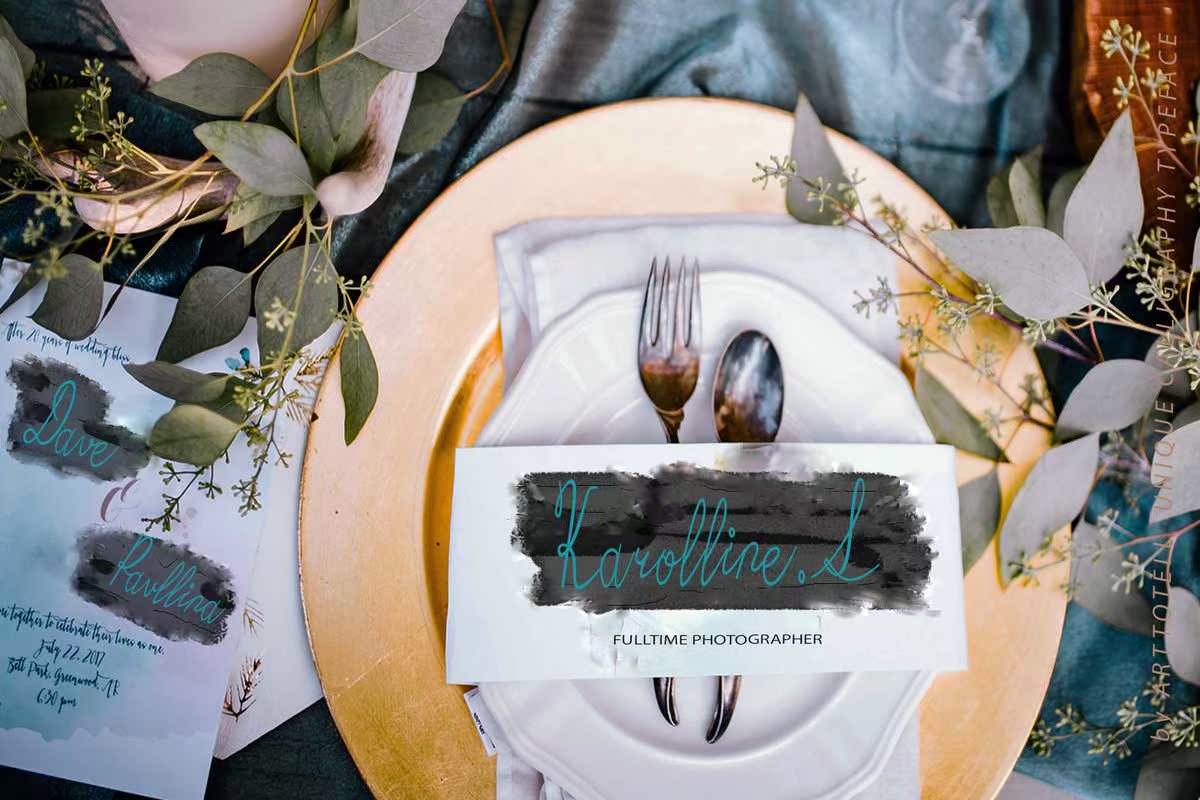
Hillaryyouthisahan和Madefont都是用爱打造的。这是一本写在MycyHomeStudio上的名著!该软件包包括对小写字符的替换,这些字符看起来像是手写的。设计为在多种设计中完美地结合了活力、网站徽标、Instagrampost和许多名字。Hillary出类拔萃,以爱心打造。这是MyczyHomeStudio特有的风格和文字!该软件包包括对小写字符的替换,这些字符看起来像是手写的。设计为可完美地在多个标志中工作,包括活力、网站徽标、Instagrampost和许多名字。